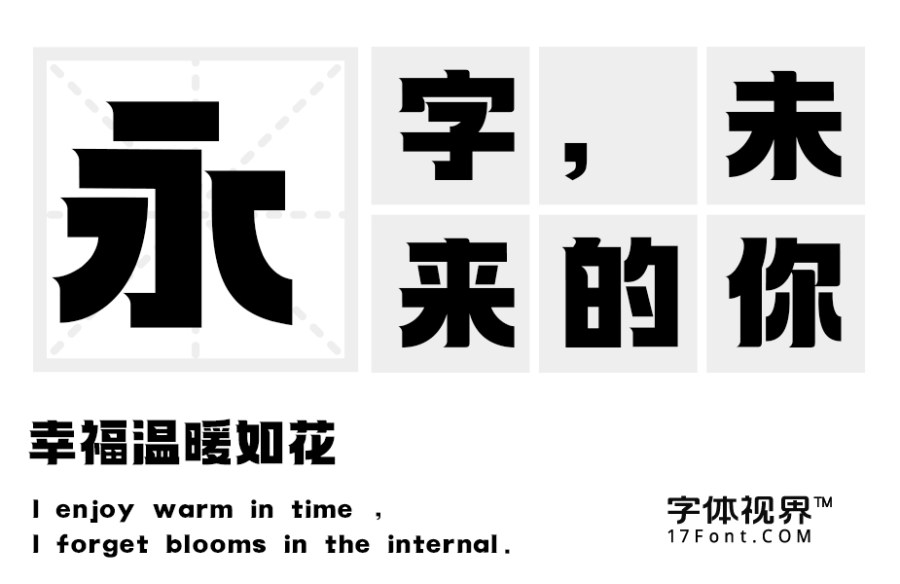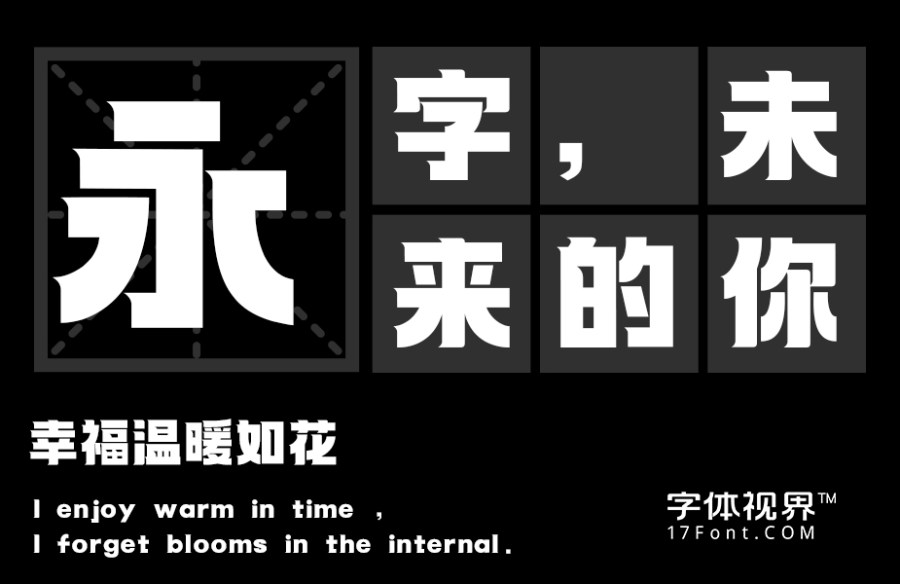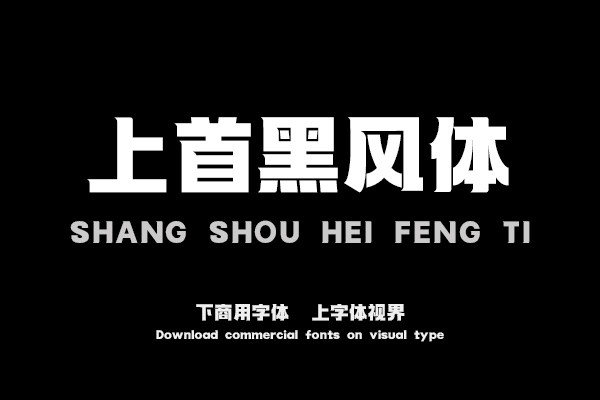
上首黑风体,简体中文约6763字,字体笔画端正。整体风格偏粗都向左方向加入了尖角设计,笔画横平竖直,一撇一捺更添柔和之感。适用于搭配标志、广告标语、商业广告等高......购买须知:“下载服务费”与“字体VIP”所获得字体 仅用于个人非商用, 商用请联系付费授权。本字体为电脑用字,手机没有root权限不支持直接手机换字(手机如何root,请自行百度搜索教程)。购买前请先 了解清楚后再付款 ,字体为虚拟产品无法回收 一旦购买不支持退款。